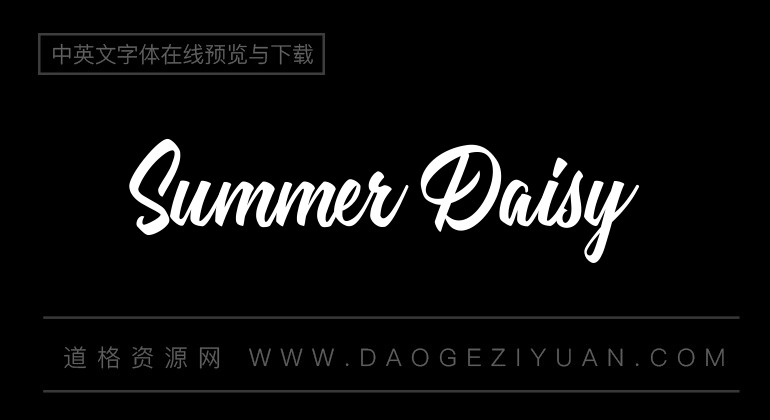
Summer Daisy
Summer Daisy 是一款简洁明快的手写字体,它充满了夏日的清新气息。它的字体设计简单而又具有可爱的外观,适合用于各种卡片、海报、标志和其他设计上的应用。它的字体设计特点是每个字母均有一个不同的曲线,使其看起来更有活力。Summer Daisy 字体的字符也比较大,使用它可以让你的文字更加明显,从而更容易被读者理解。
Summer Daisy是一款非常不错的手写艺术字体,具有很好的视觉感,适合于文化类的宣传设计、商业类品牌的广告和产品包装设计以及个性化文字排版等较多场景。